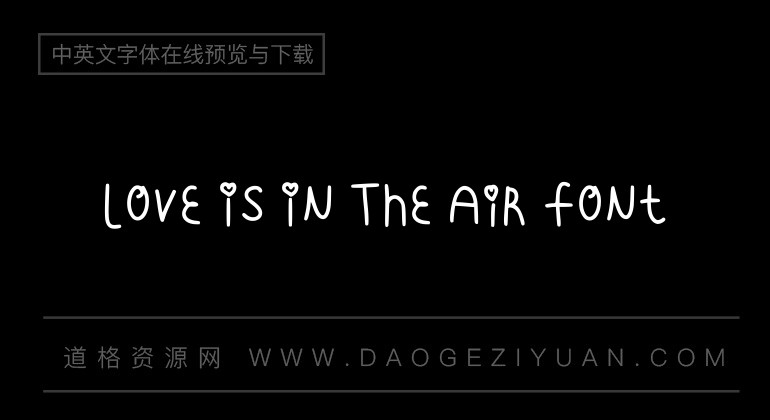
Love Is In The Air Font
Love Is In The Air Font 是一种浪漫的手写风格字体,适用于设计情人节、婚礼、生日、纪念日等场合的卡片、海报、贺卡、标语等设计。该字体的特点是具有优雅的笔画,独特的风格和良好的可读性。它由字母、数字、标点符号和一些特殊符号组成,其中每个字符都用手写风格绘制,呈现出亲切、温馨和浪漫的气息。Love Is In The Air Font 可以免费下载使用,支持在 Mac 和 Windows 操作系统下使用。
Love Is In The Air Font是一款非常不错的手写艺术字体,具有很好的视觉感,适合于文化类的宣传设计、商业类品牌的广告和产品包装设计以及个性化文字排版等较多场景。